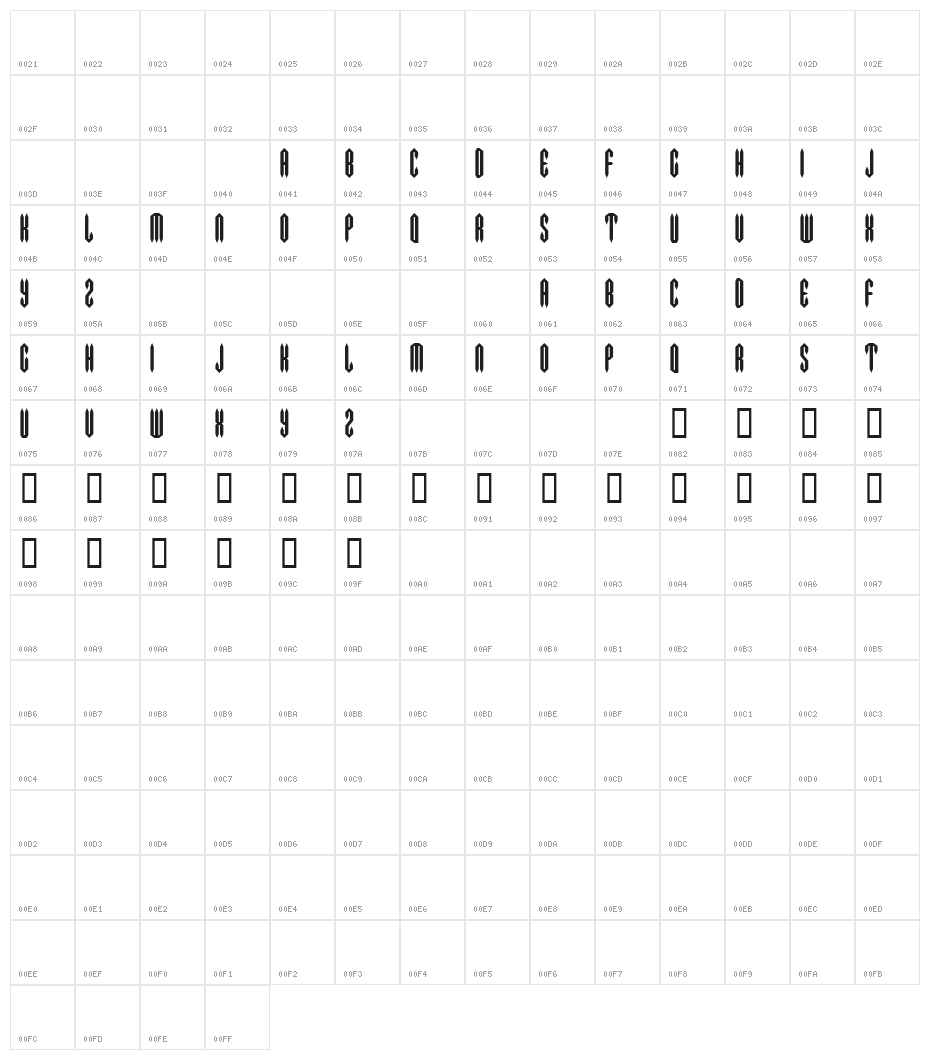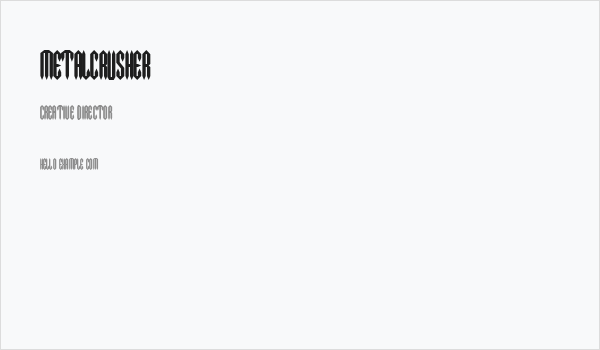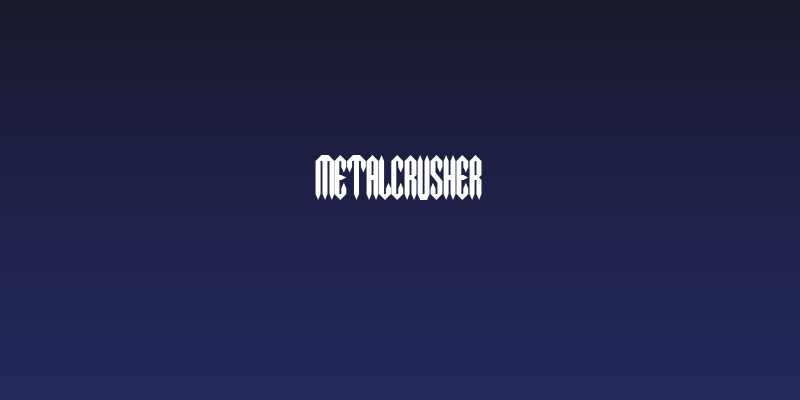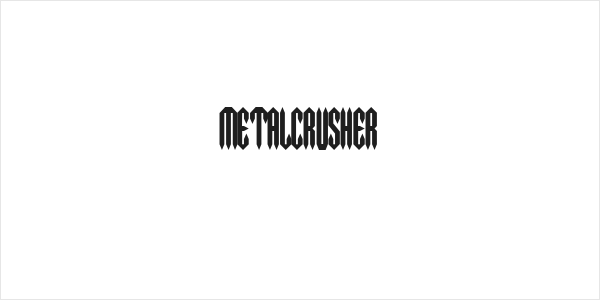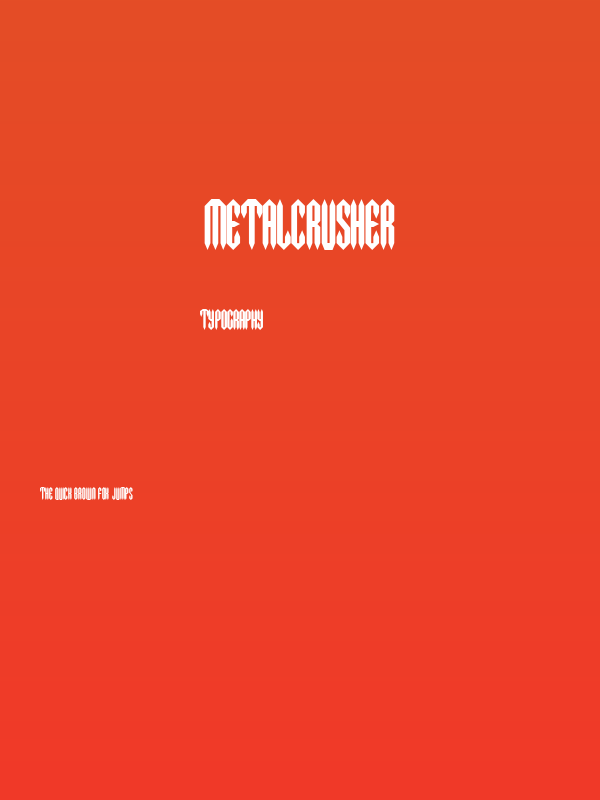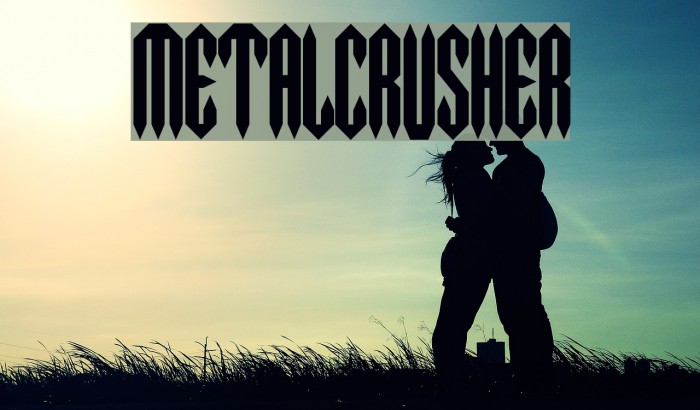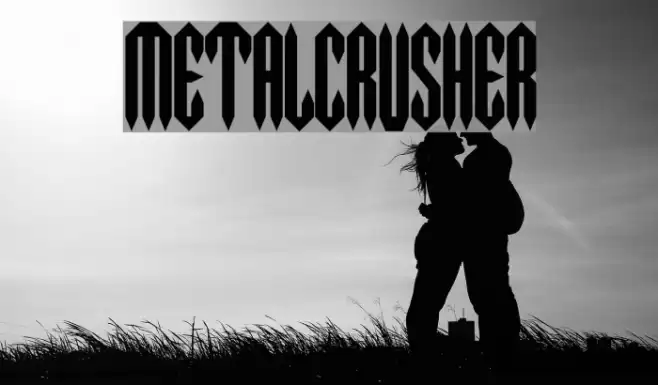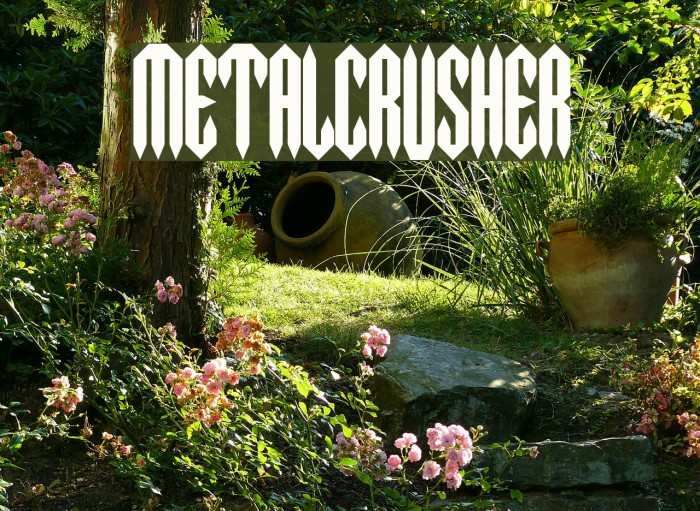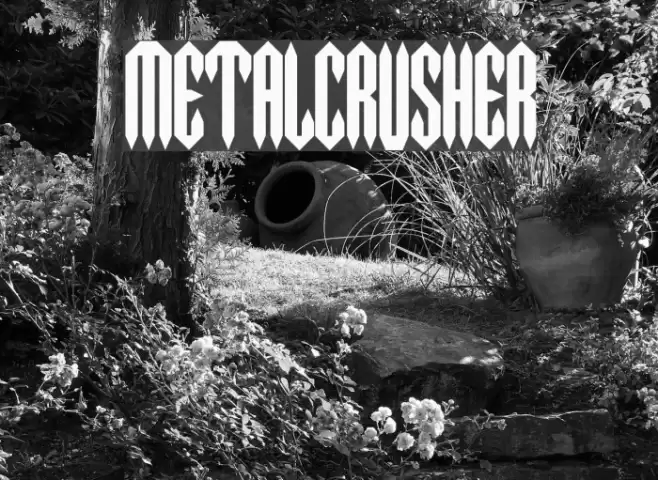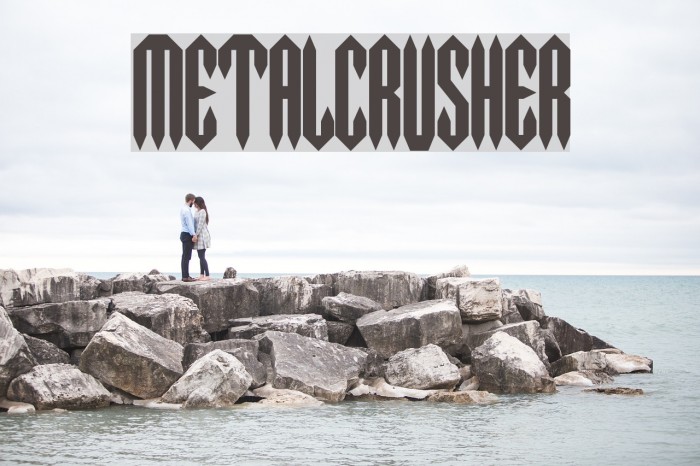
MetalCrusher Font
✎ Gothic
| Progetti proposti | Ideal for music album covers, video game titles, posters, and branding that requires a strong, modern aesthetic. |